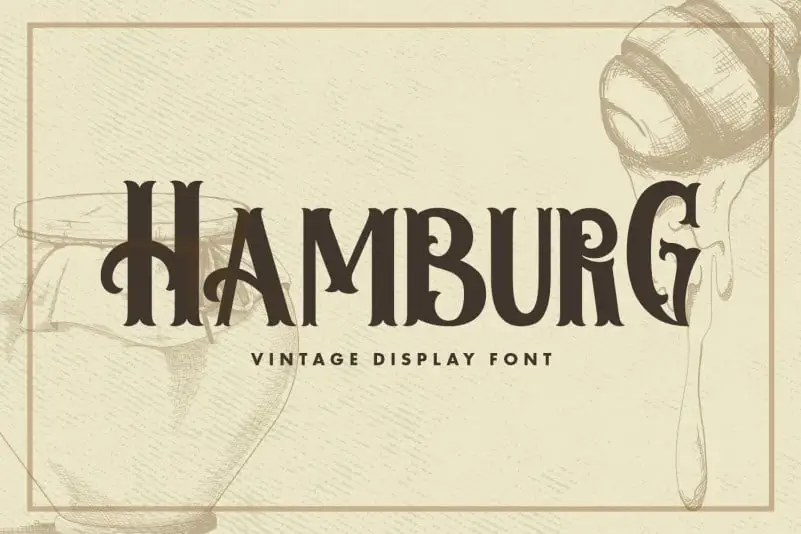
Hamburg Vintage Style Font – Download Grátis
Introduzimos a Hamburg Vintage Style Font, uma fonte à estilo vintage perfeitamente projetada para aplicação em diversos ambientes onde a elegância dos anos 50 e 60 é valorizada. Esta fonte é ideal para criações que precisam de um toque único e sofisticado, como logotipos, revistas, menus, rótulos, embalagens e materiais promocionais. Seja ela uma seleção perfeita para aplicar em suas campanhas publicitárias, cartões de visita ou até mesmo em sua próxima coleção de moda. A Hamburg Vintage Style Font é a escolha certa quando você busca um visual clássico e contemporâneo que destacará sua marca ou produto. Ela adicionará um toque elegante e retro a qualquer projeto, seja ele digital ou impresso. Seja na hora de criar um design minimalista para revistas modernas, ou em uma atmosfera mais sofisticada com cartões de visita bem elaborados – esta fonte tem o poder de transformar sua marca de forma imediatamente reconhecível. Com a Hamburg Vintage Style Font do Designer typotopia, você não apenas está adquirindo uma ferramenta versátil e elegante, mas também uma maneira singular de expressar seu estilo, seja ele fashionista ou de moda pura. Afinal, quem sabe quando encontrará algo tão lindo na sua jornada criativa?